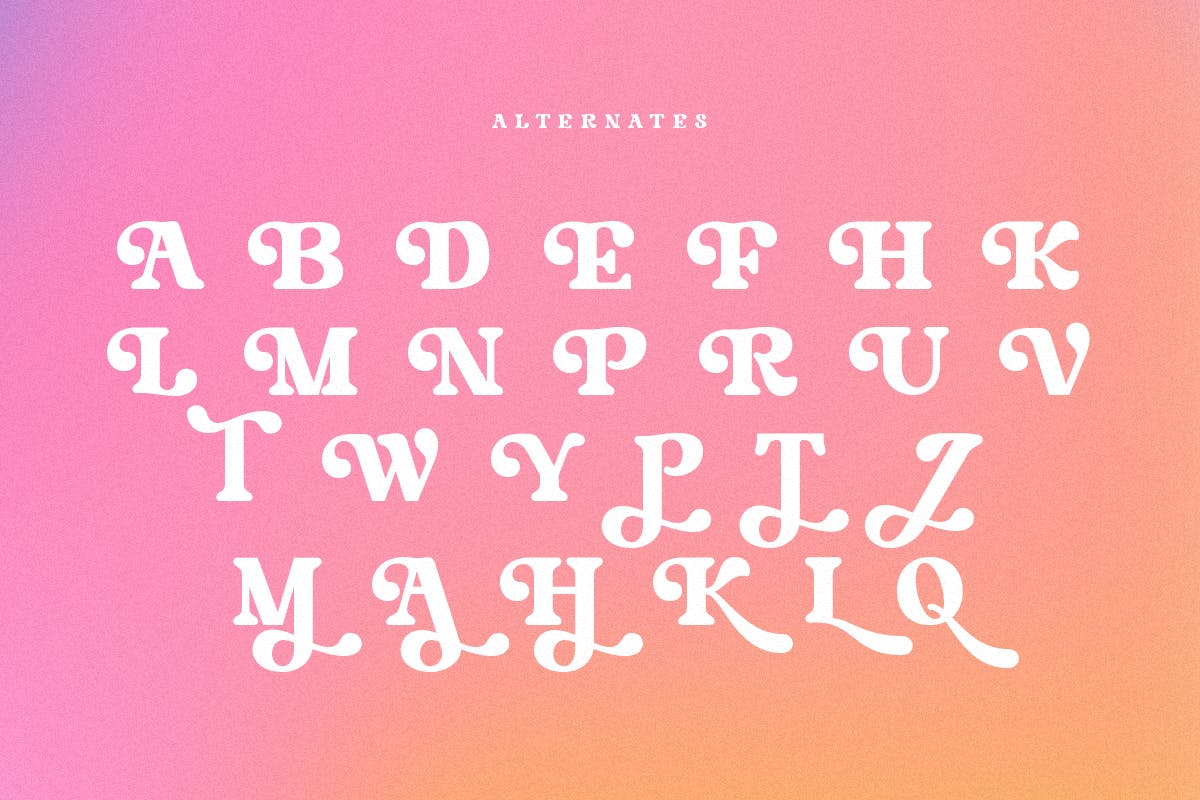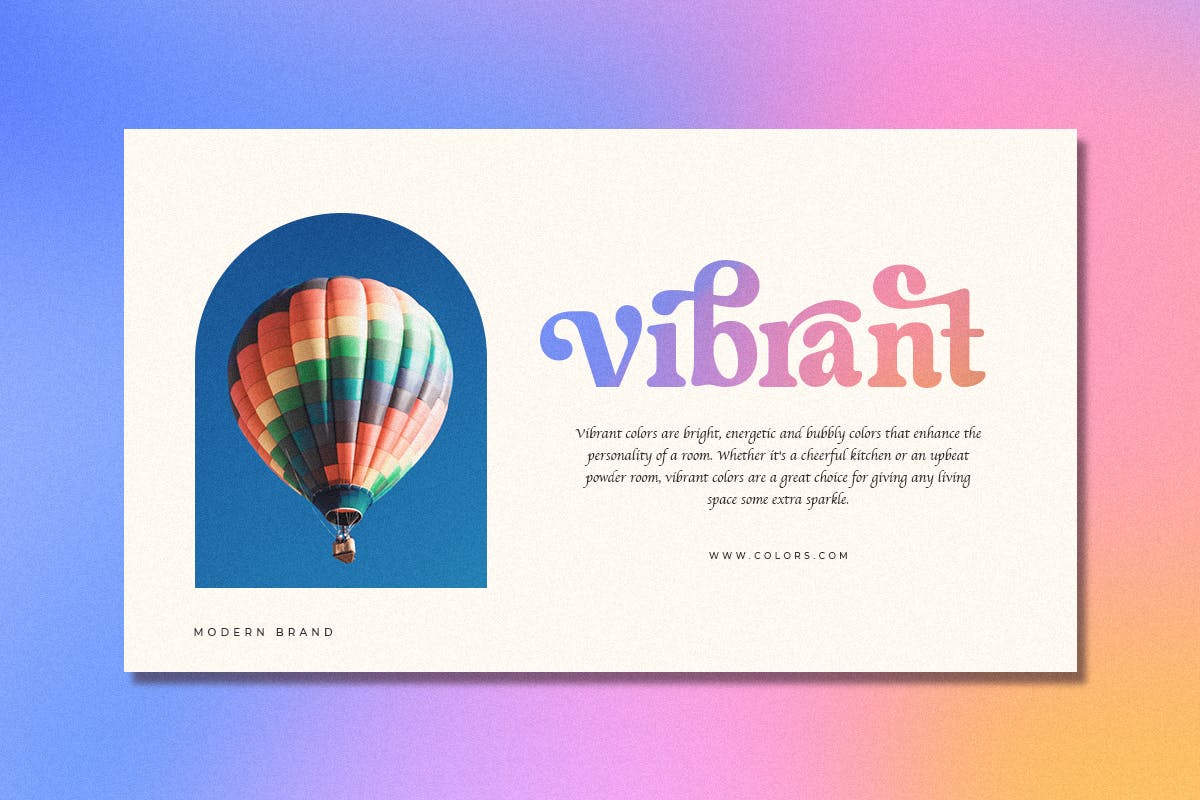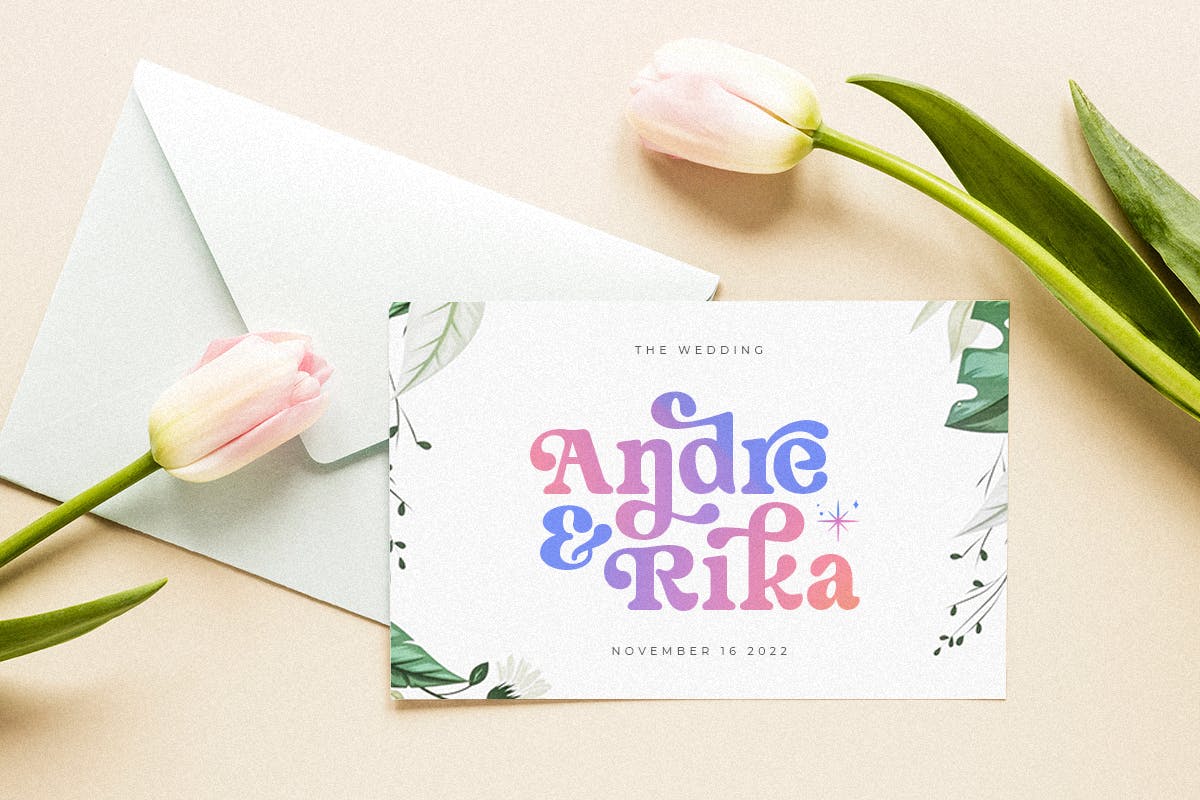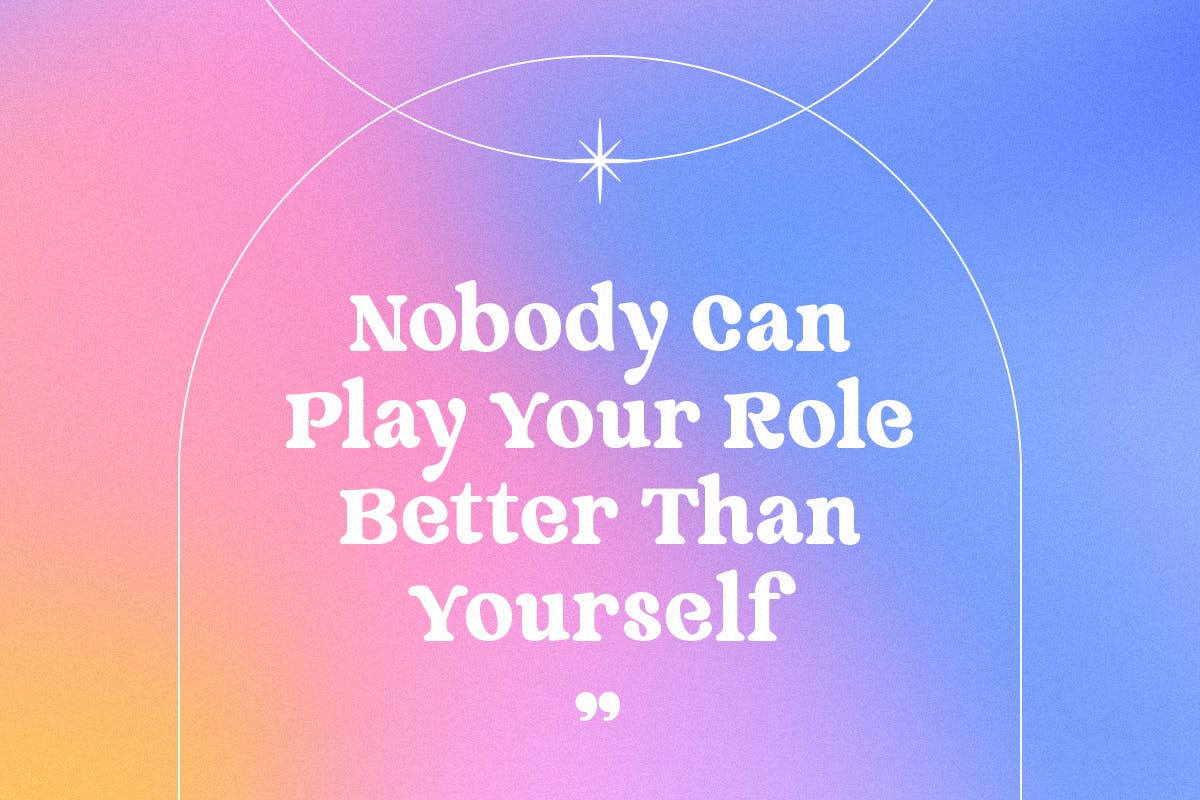
فونت Rainbow یک فونت مدرن و وینتیج است
این فونت وینتیج جدید بهطور خاص برای نیازهای برندینگ منحصر به فرد ایجاد شده است و شامل لیگاتورهای اضافی در سبک خاصی است که آماده است تا به ارزش برند شما اضافه کند. این فونت به طراحان و صاحبان محصولات کمک میکند تا طراحیهای خود را منحصر به فرد و وینتیجتر کنند.